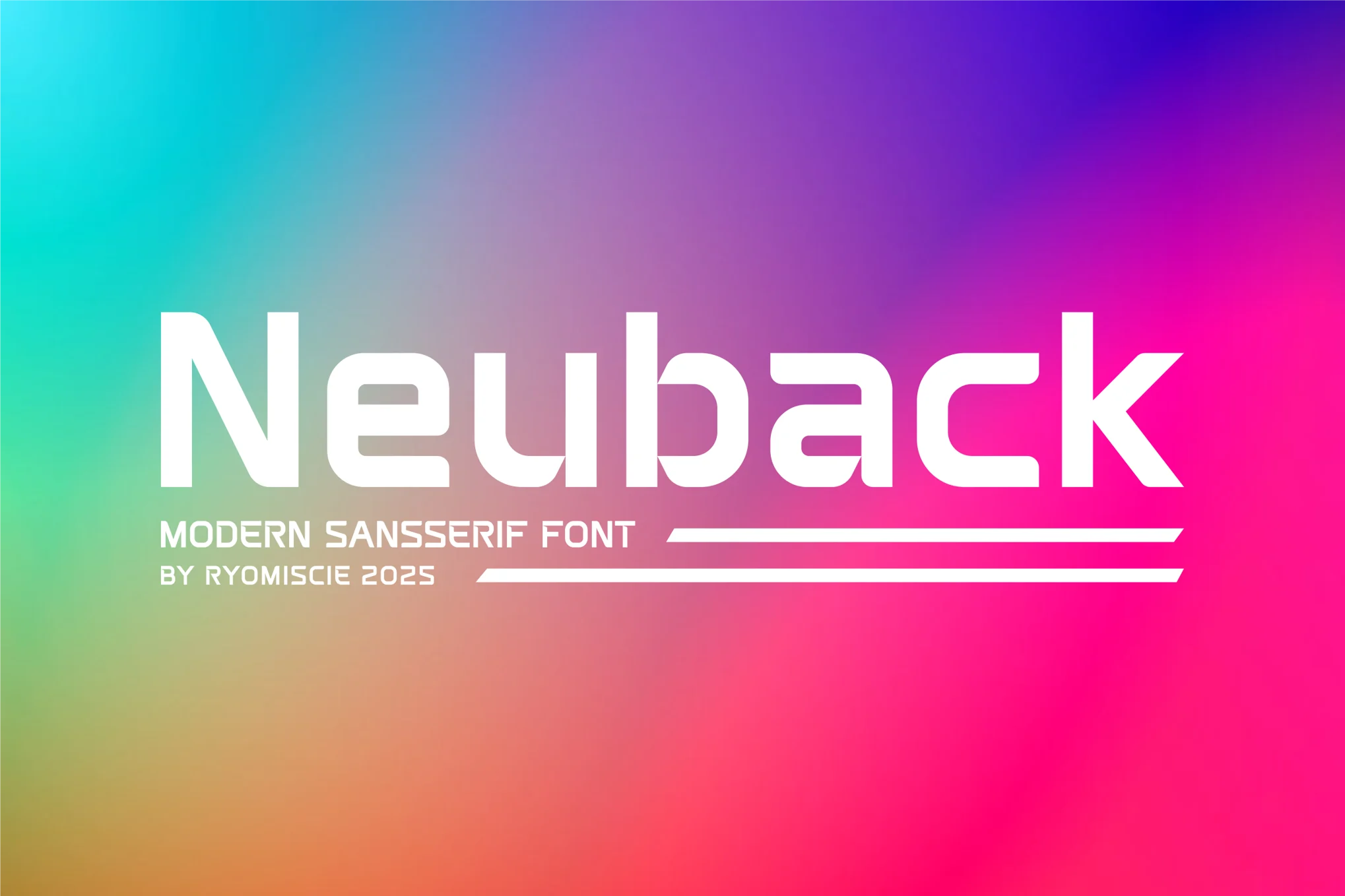
دانلود فونت Neuback – Modern Sans Serif Font
Neuback Font- Modern Font یک فونت نمایشگر برجسته و معتبر است. این فونت برای هر پروژه برندسازی مانند لوگو، چاپ تی شرت، esport و بسیاری موارد دیگر مناسب است. برجسته در طیف گسترده ای از زمینه ها.